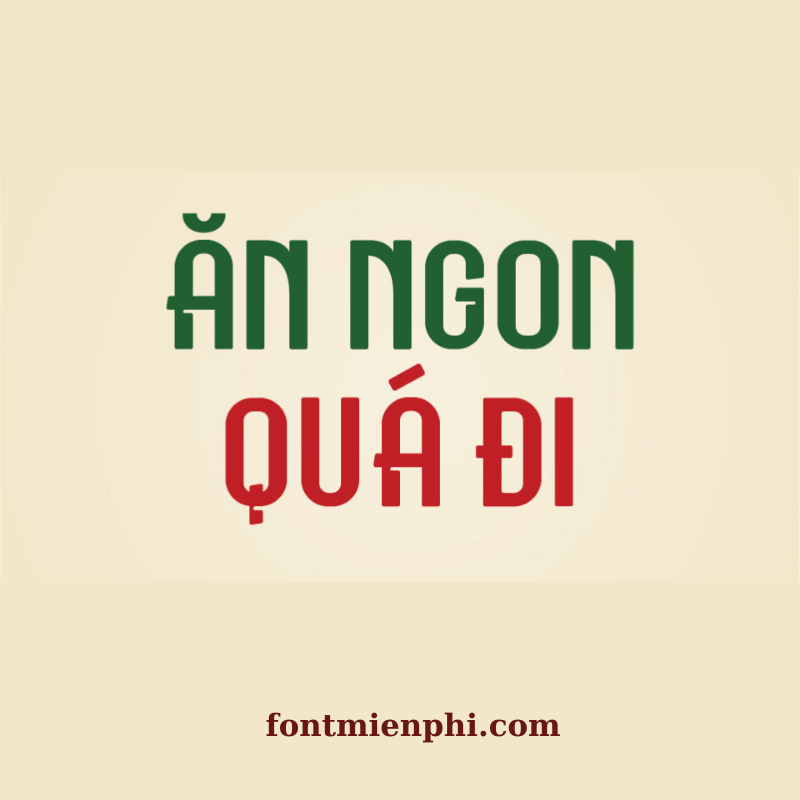
Font Việt hóa 1FTV VIP Meholrax
Font Việt Hóa 1FTV VIP Meholrax – Phong Cách Độc Đáo Cho Thiết Kế
Giới Thiệu
Font Việt hóa 1FTV VIP Meholrax là bộ font chữ độc quyền, được thiết kế dành riêng cho cộng đồng sáng tạo Việt Nam. Với phong cách hiện đại, nét chữ sắc sảo và khả năng tương thích tiếng Việt hoàn hảo, Meholrax trở thành lựa chọn hàng đầu cho dân thiết kế, content creator và marketer.
Đặc Điểm Nổi Bật
• Thiết kế độc đáo: Nét chữ cá tính, phù hợp với poster, logo, banner quảng cáo.
• Hỗ trợ tiếng Việt: Đầy đủ dấu, không lỗi font khi sử dụng trên mọi nền tảng.
• Đa dạng phong cách: Từ thanh lịch đến phá cách, đáp ứng mọi nhu cầu thiết kế.
Ứng Dụng
1FTV VIP Meholrax phù hợp cho:
• Thiết kế đồ họa, in ấn.
• Content social media, video.
• Branding, quảng cáo.
Kết Luận